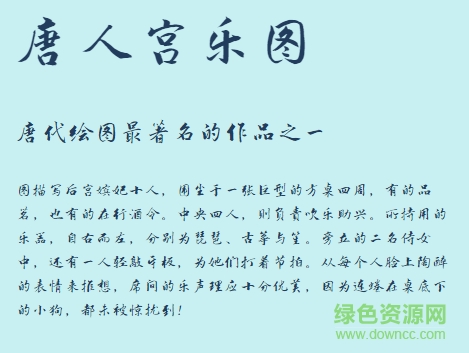
文鼎dc云康行楷是文鼎字體推出的一款行楷書字體,結(jié)合行書和楷書的特點,讓字體兼具端正和飄逸之美,喜歡的朋友來綠色資源網(wǎng)下載使用吧!
文鼎DC云康行楷體_B,由知名書法家_施隆民教授真跡手寫,文鼎作字型數(shù)字化,是一套原汁原味的書法真跡字型。 云康行楷的字型特色,是加入「迭字」功能,施隆民教授在書寫時,特意創(chuàng)作「相同字的不同寫法」,以展現(xiàn)書法中「不雷同」「不重復(fù)」的變化美感,讓「變化」更能呈現(xiàn)書法藝術(shù)的精神。此外,云康行楷提供了兩種不同書法風(fēng)格作選擇,其中云康行楷碑帖版,藉由部首共享 、改變寫法、增減筆畫等多方式,保留傳統(tǒng)書法運筆藝術(shù)之美。
「云康行楷」旨在掌握書法美感,在筆法上以流暢、生動為原則;在結(jié)構(gòu)上為了排版印刷的美觀,盡量保持「端莊」的體態(tài),希望借由此套字型的推出,將中國書法藝術(shù)之美帶入文字設(shè)計應(yīng)用的領(lǐng)域之中,同時也可以促進字型設(shè)計的多元化。